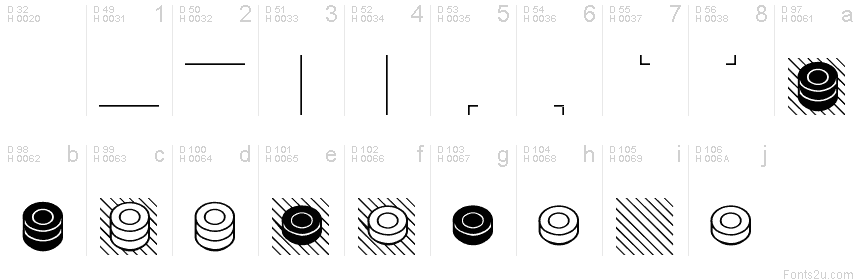
Font Draughts Utrecht zamienia proste czarno-białe pionki do gry w warcaby w wyraziste piktogramy, które są czytelne na pierwszy rzut oka. Solidne dyski – pojedyncze lub ułożone w stos – sprawiają wrażenie masywnych i namacalnych, dzięki czemu symbole te doskonale sprawdzają się wszędzie tam, gdzie trzeba wyjaśnić ruchy, pozycje lub stan gry bez użycia tekstu. To darmowy font, w którym stawiamy na przejrzystość, a nie na dekoracyjność.
Ten darmowy font świetnie sprawdza się w instrukcjach do gier planszowych, diagramach, materiałach edukacyjnych, poradnikach strategicznych i blogach o grach. Nadaje się również do ikon interfejsu w aplikacjach czy na minimalistycznych plakatach, gdzie jeden symbol musi nieść konkretny przekaz. Draughts Utrecht najlepiej łączyć z czystym krojem bezszeryfowym w mniejszych rozmiarach, aby ikony pozostały dominujące wizualnie i łatwe do zrozumienia.